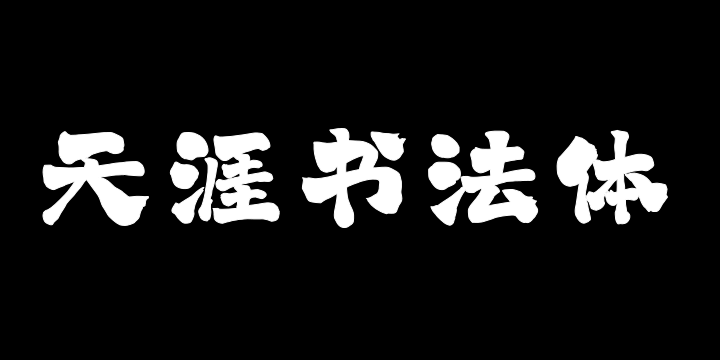
上首天涯书法体 By 上首造字 商用字体
字体全名: 上首天涯书法体
铸字厂: 上首造字
设计师: 胡博剑
字体简介: 上首天涯书法体,笔法灵动,笔画形态富有变化,起笔、行笔、收笔处模拟传统毛笔书写韵味,或藏锋蓄势,或露锋显锐,提按转折间尽显灵动自然,规避机械刻板之感。结构稳健,在遵循汉字结构规律基础上,适度夸张与变形,重心平稳又不失活泼,部分笔画巧妙穿插、呼应,增强整体视觉张力与和谐感。适用于搭配标志、广告标语、商业广告等高端属性。